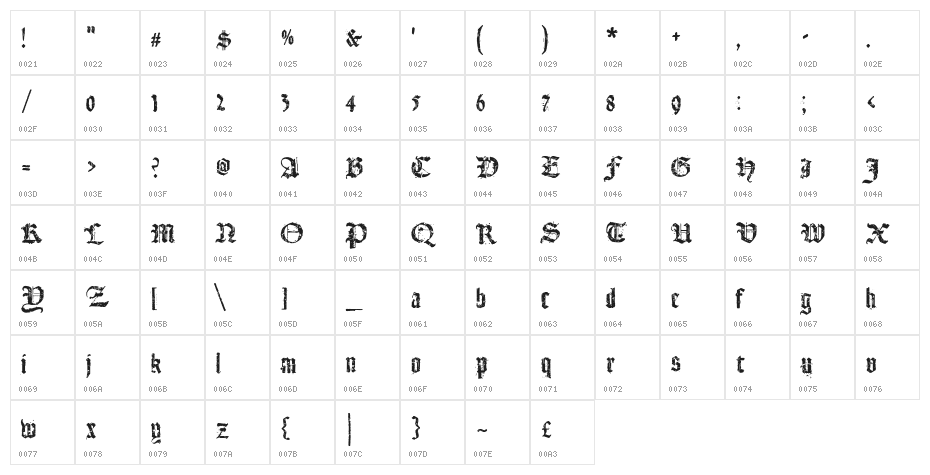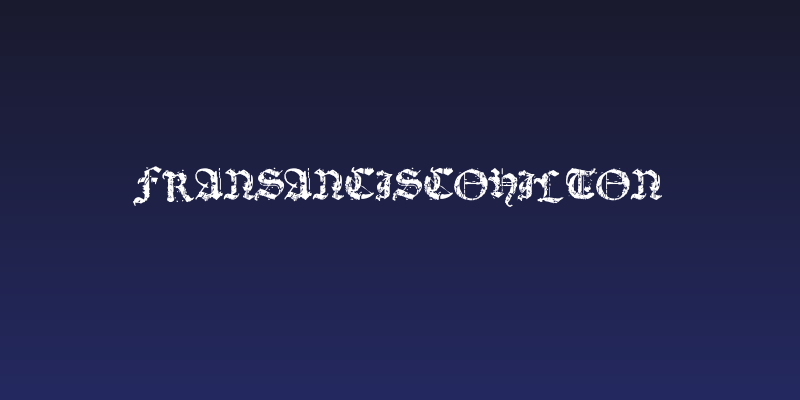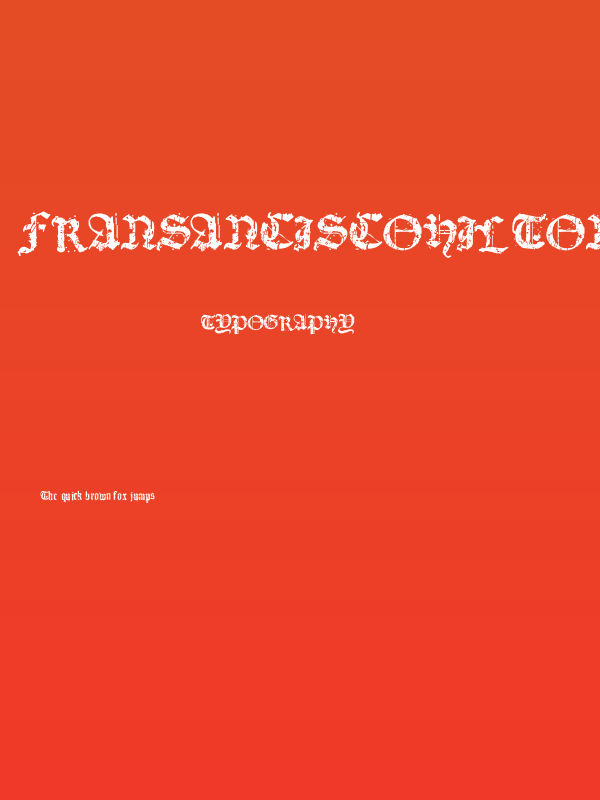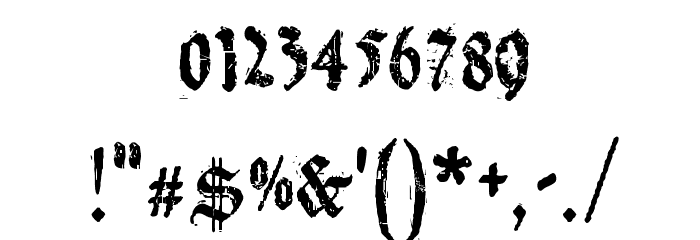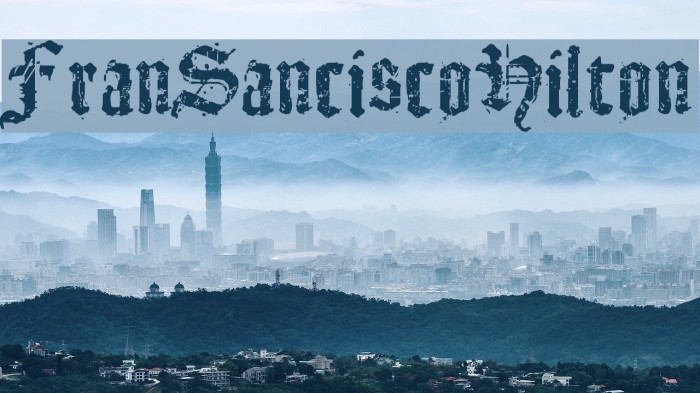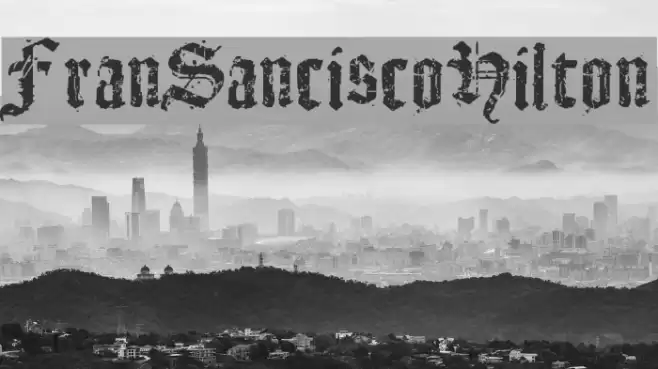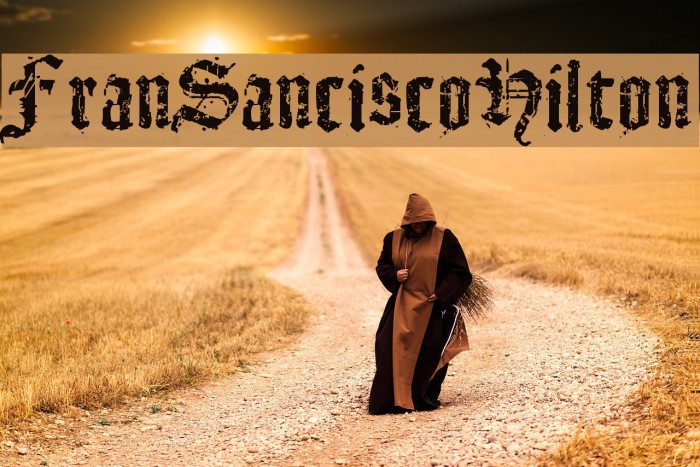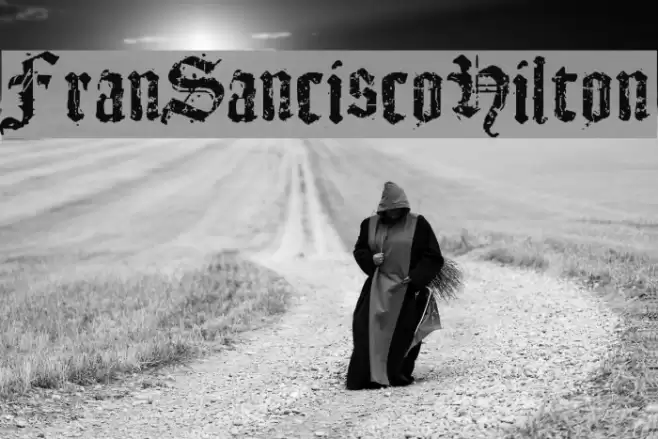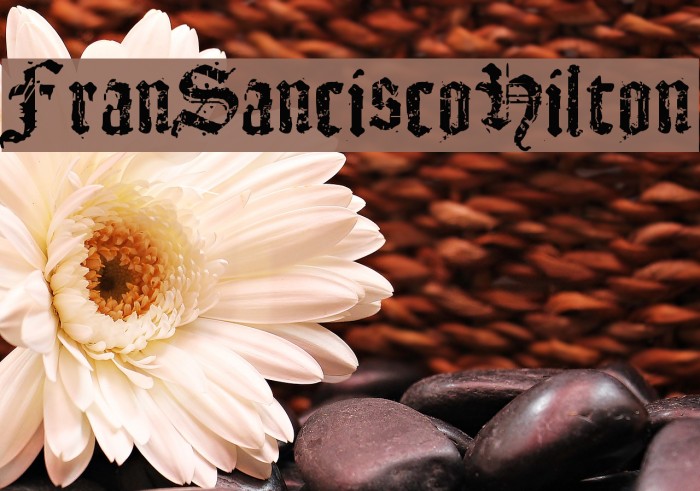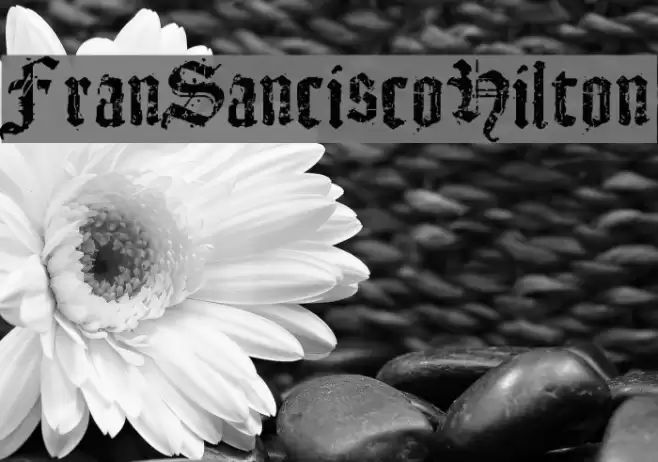
FranSanciscoHilton Font
✎ Gothic
| Kategorien | Gothic |
| Gesamtstil | Vintage, Decorative |
| Anwendungsfall | Logos, Headlines, Posters |
| Vorgeschlagene Projekte | Ideal for album covers, posters, branding for edgy or vintage-themed products, and any design requiring a bold, historical touch. |